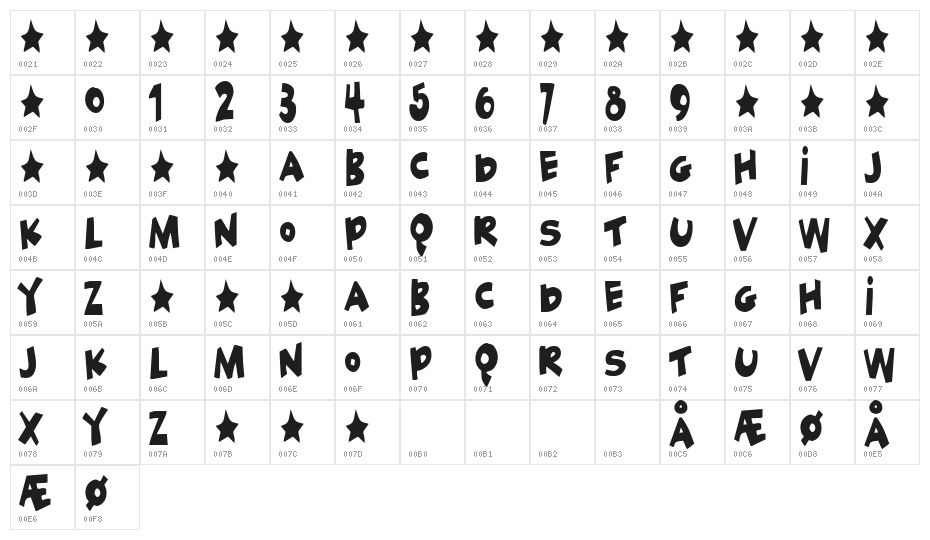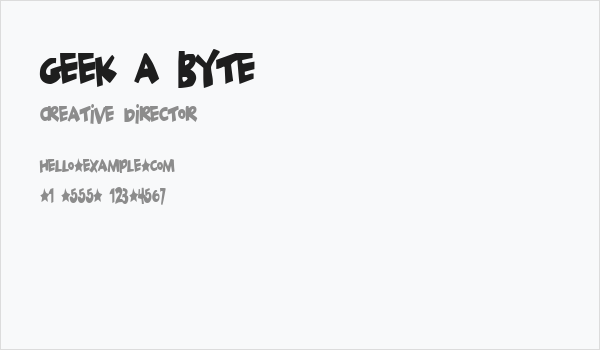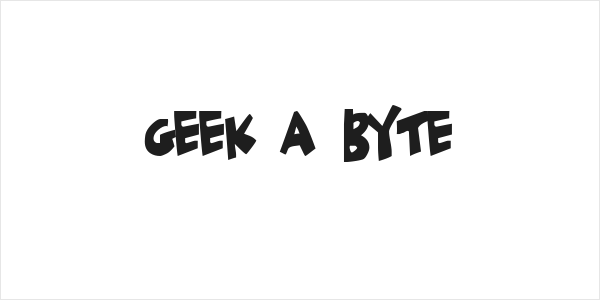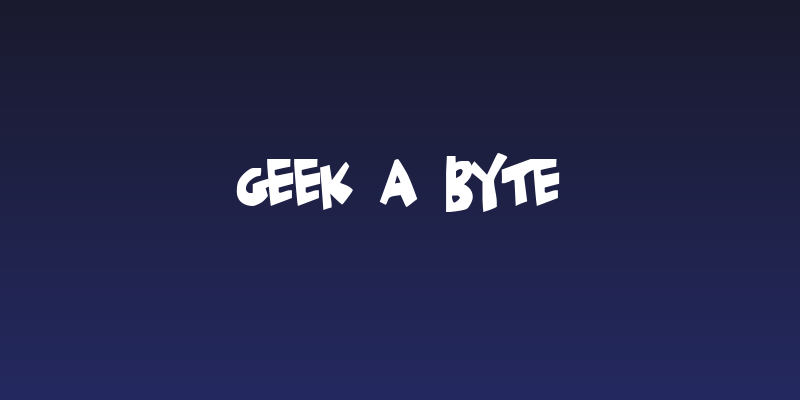
Geek a byte Font
| Stile generale | Playful and Cartoonish |
| Progetti proposti | Ideal for children's books, comic strips, playful branding, and party invitations. |